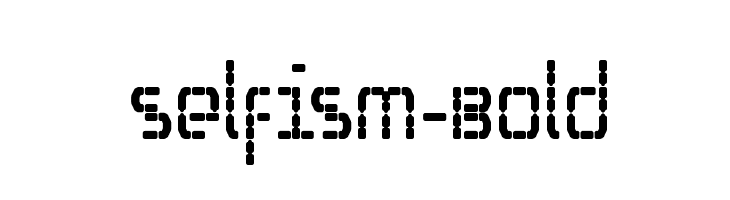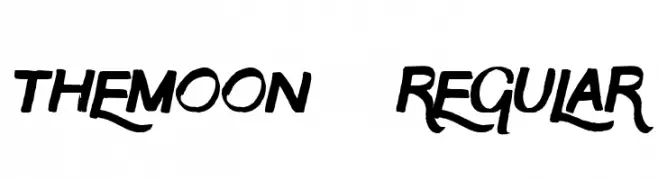
欢迎来到 最新字体 专区——在这里你能发现 FFonts.net 新增的精选字库。 无论你是设计师、开发者,还是字体爱好者,这个页面都能帮助你紧跟趋势。
每款 新字体 都有独特个性:从干净现代的无衬线到富有表现力的手写体、醒目的展示体。 我们频繁更新列表,你可以先在线预览再免费下载使用。
( Fonts by Alex Tomlinson - Skyhaven Fonts - shfonts.com )
A bold, expressive font with dynamic curves and sharp edges.
( Fonts by Alex Tomlinson - Skyhaven Fonts - shfonts.com )
A playful, handwritten font with tall, narrow letters and a casual style.
( Fonts by Alex Tomlinson - Skyhaven Fonts - shfonts.com )
A bold, hand-drawn font with a sketch-like, textured appearance.
( Fonts by Alex Tomlinson - Skyhaven Fonts - shfonts.com )
A playful, hand-drawn font with tall, narrow letters and a whimsical style.
( Fonts by Alex Tomlinson - Skyhaven Fonts - shfonts.com )
A modern, geometric font with clean lines and rounded edges.
( Fonts by Alex Tomlinson - Skyhaven Fonts - shfonts.com )
A modern font combining geometric uppercase with cursive lowercase styles.
( Fonts by Alex Tomlinson - Skyhaven Fonts - shfonts.com )
A playful and artistic font with elongated, whimsical strokes.
( Fonts by Alex Tomlinson - Skyhaven Fonts - shfonts.com )
A whimsical and decorative font with intricate curls and swirls.
( Fonts by Alex Tomlinson - Skyhaven Fonts - shfonts.com )
A dynamic and fluid script font with elegant, flowing letterforms.
( Fonts by Alex Tomlinson - Skyhaven Fonts - shfonts.com )
A playful and dynamic script font with fluid, slanted letterforms.
常见问题 — 最新字体
现在大家都在用哪些新字体?
流行变化很快,但极简无衬线与个性鲜明的展示体当前更受欢迎, 特别适合移动端内容与现代品牌风格。
有哪些值得尝试的 5 款新字体?
近期热门包括 TheMoon-Regular, ClarksSummit, SketchbookNasty-Regular, IceCreamSandwich-Regular and MetroSkies-Regular 它们在清晰度与个性之间取得平衡,适用于科技品牌、编辑排版与社媒视觉。